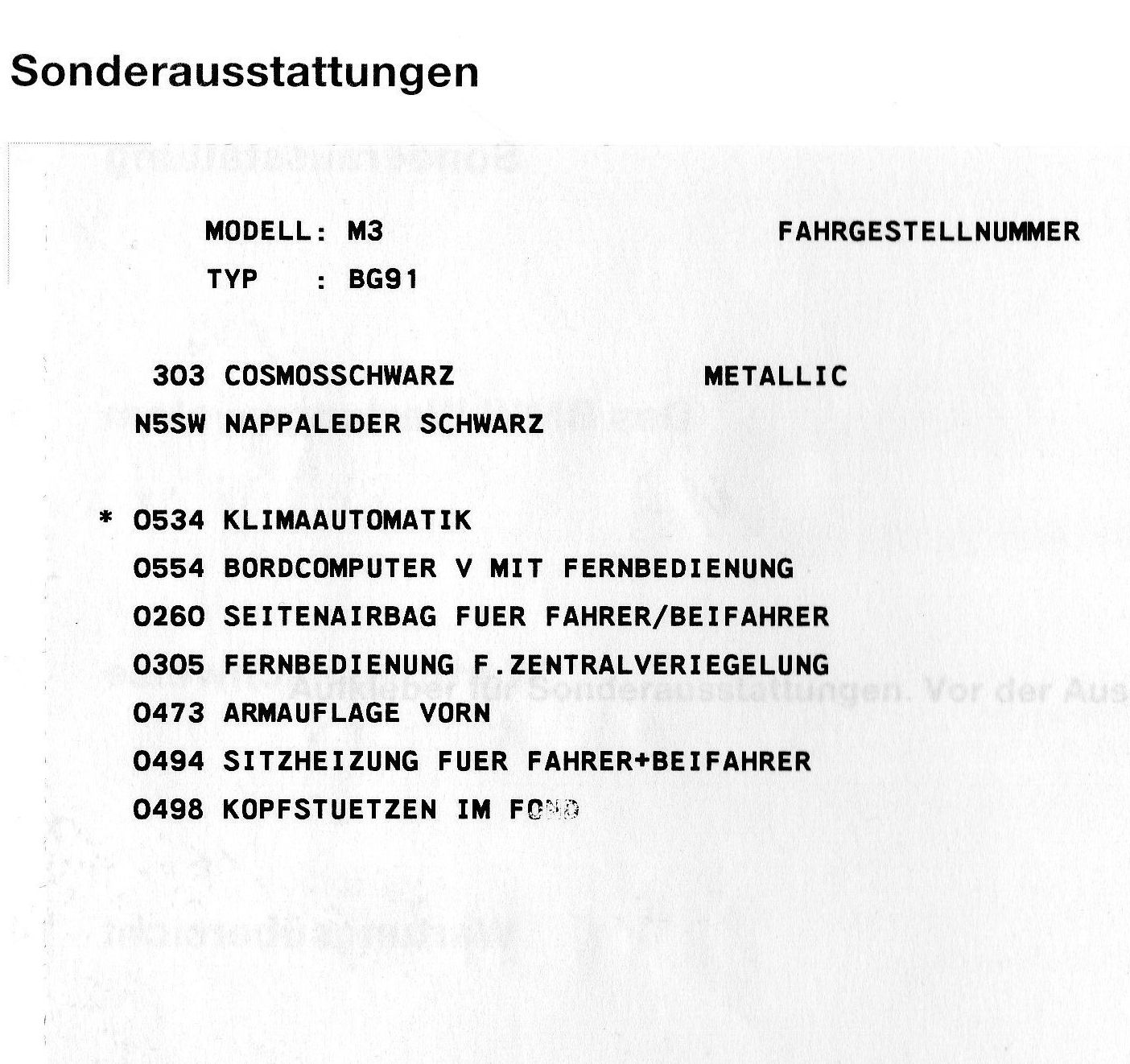
Welche Schriftart ist das?
Bertel hat ja schon das wichtigste gefragt. Ansonsten geht die Schrift Richtung Helvetica Monospaced Bold, aber ohne weitere Hintergrundinformationen und nur auf der Basis des Beispielbildes kommt man da nicht unbedingt sehr viel weiter. Den Bitstream-Klon der Helvetica Monospaced findet man auch als Monospaced 821 BT in den verschiedenen Bitstream-Schriftensammlungen, die bei verschiedener Corel-SW (u.a. Corel Draw) mitgeliefert wird.
Diese Schriftart wird von BMW verwendet, es ist aus einem Auszug von einem Serviceheft.
Uwe, die sieht aber doch ganz anders aus … :-? Und in dem von Joshua verlinkten PDF ist auch keine Monospaced enthalten, wenn ich das richtig sehe.
Ich gehe davon aus dass es wohl auch eine passende Monospace geben wird. Oder liege ich da falsch?
In dem PDF müsste sie dann aber doch eigentlich mit drin sein. Da wird ja schließlich die Schrift und ihre Anwendung erläutert.
Das ist doch die, auf die Joshua verlinkt hatte, oder? In dem PDF ist allerdings keine Monospaced enthalten. Aber es kann ja gut sein, dass BMW diese Schnitte komplett unterm Deckel hält und niemand außer den Leuten, die die technischen Handbücher zu den Fahrzeugmodellen schreiben, darauf Zugriff hat.
Ich vermute eher dass das eine druckerspezifische Schrift ist, die einfach irgendeinem Labeldrucker entspringt. Für die Endkundenaugen ist sie ja nicht bestimmt, daher denke ich dass da nicht unbedingt ein dem Corporate Design entsprechender verwendet wird.